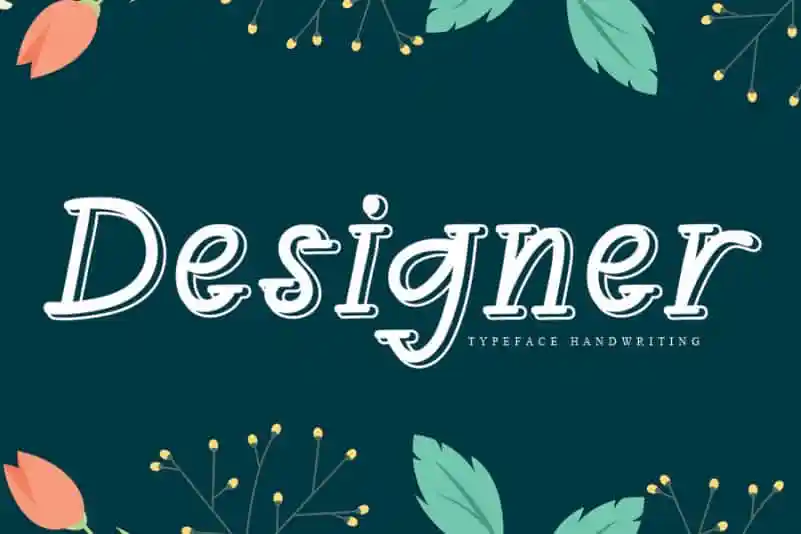
Designer Display Font
Essa fonte Designer Display é uma criação exclusiva do andikastudio para você, oferecendo experiências impressionantes. Ela captura o espírito handwritten com detalhes cuidadosamente trabalhados, proporcionando um toque único e pessoal aos seus projetos. Suas linhas delicadas e acentos naturais dão à sua escrita uma vivacidade realística que vai muito além de fontes digitais convencionais. Ideal para designers buscando adicionar um elemento autêntico ao seu trabalho, esta fonte Designer Display é certamente o recurso gráfico perfeito para capturar a atenção de seus clientes e destacar sua criação única no mercado.